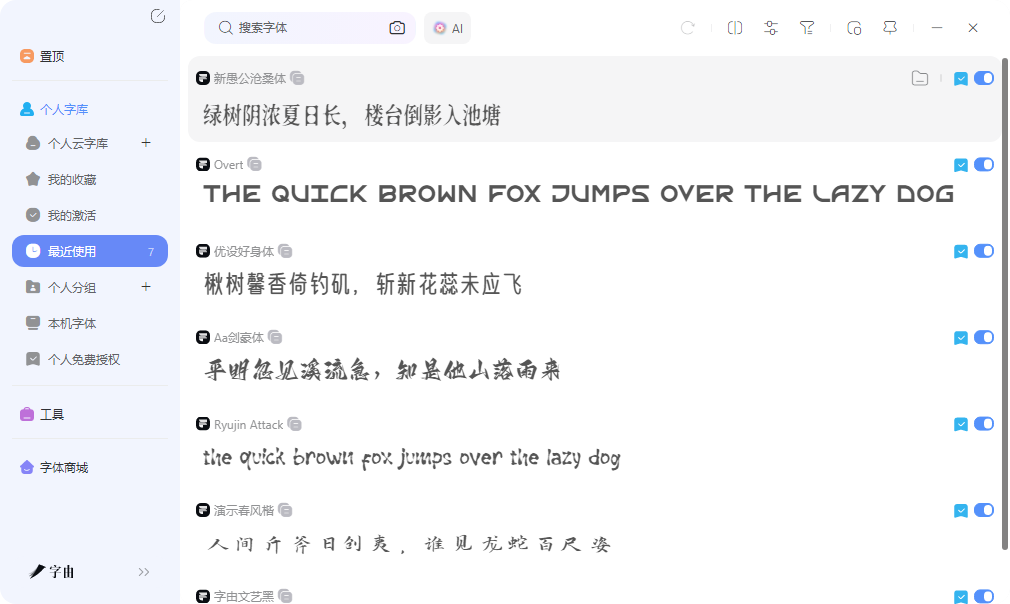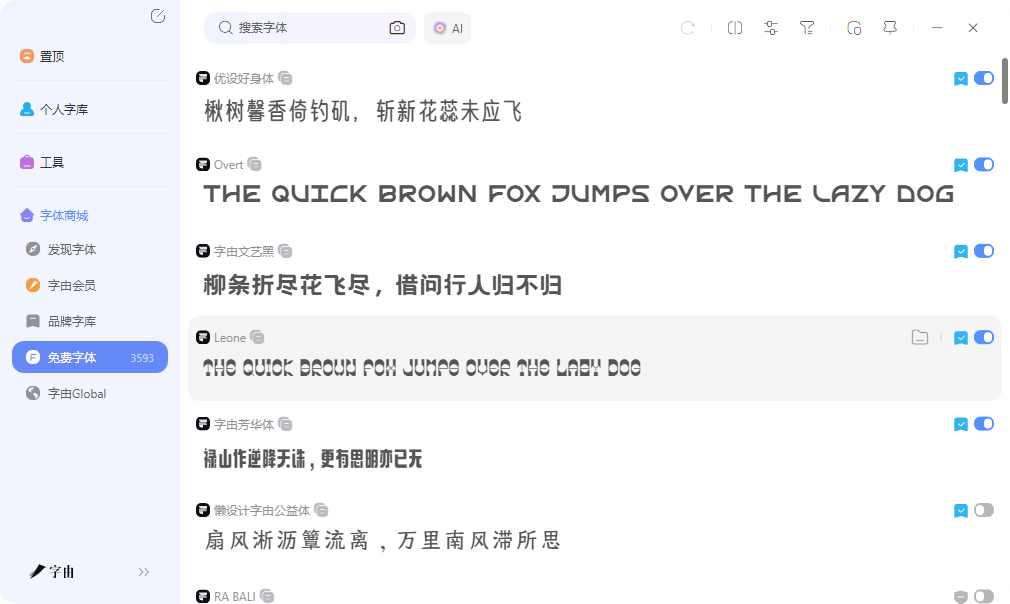
免费的字体下载网站,海量资源加精选推荐
很多人找字体时有个习惯,打开收藏夹里十几个网站逐个翻,最后下载了一堆重复的资源,硬盘里存了上千款字体,真到用的时候还是不知道选哪个。更麻烦的是授权问题,有些字体看着免费,实际仅限个人使用,真用到商业项目上才发现要补费用。其实找字体不是越多越好,关键是渠道靠谱、分类清晰、授权明确。这篇文章整理了五个免费的字体下载网站,从海量开源库到精选独立厂牌都有覆盖,帮你缩小搜索范围,把时间花在设计本身而不是找字上。
字由在字体管理上的思路比较贴近实际工作流,设计师通常同时处理多个项目,每个项目的字体需求不一样,A项目要商务黑体,B项目要文艺手写体,C项目要科技感的无衬线体。字由的收藏分组功能可以按项目建立独立的字体文件夹,把每个项目常用的几款字体归到一起,切换项目时直接打开对应分组,不需要在庞大的字体库里重新翻找。分组名称可以自定义,比如电商大促、品牌VI、社交媒体等,一目了然。
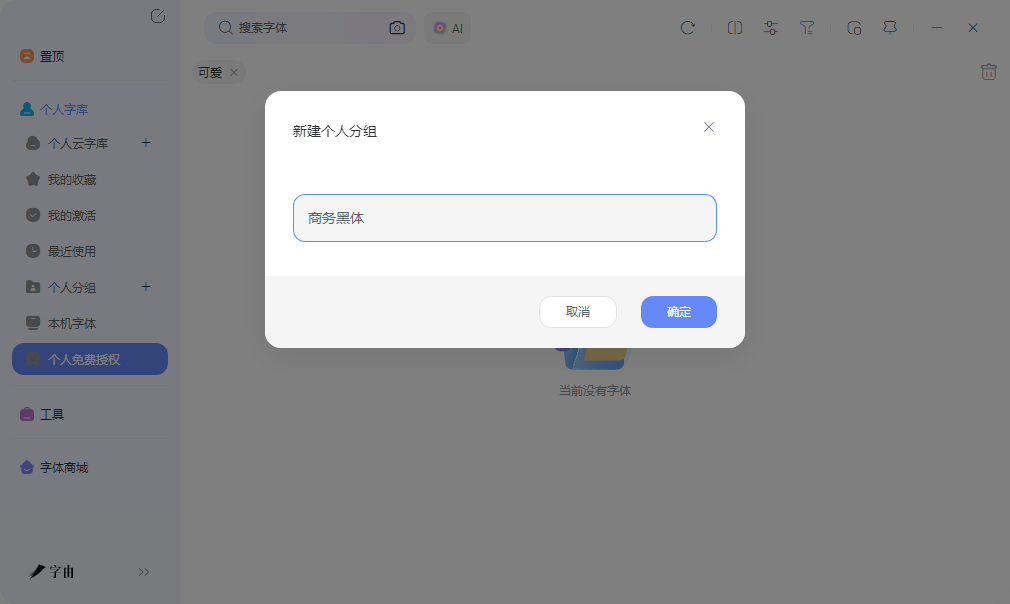
网页版和客户端的数据是互通的。习惯在浏览器里浏览的人可以先在网页版里看到合适的字体,点收藏后,打开客户端就能直接激活使用。反过来在客户端里收藏的字体,网页版里也能看到。这种双端协同让找字和用字不需要绑定在同一台设备上,临时在其他电脑上打开浏览器就能浏览和收藏,回家再激活使用。对于经常在不同设备之间切换的设计师来说,这种灵活性比较实用。
免费商用的字体超过三千款,卡片上直接标注授权类型。对于需要快速确认能不能商用的场景,这个标注省了不少时间。这些字体来自优设、阿里妈妈、汉仪、蒙纳等正规厂商,上架前经过授权审核,企业用户用起来比较放心。预览框支持输入中文文案,调整字号和背景色,看到真实效果再决定是否加入收藏分组,避免了收藏后发现不合适再删除的反复操作。
2、Open Foundry
Open Foundry是一个开源字体平台,定位偏向精选而非海量。平台上的字体数量不算多,但每一款都经过筛选,品质比较高。字体风格偏向现代设计,很多适合做网页、界面和品牌视觉项目。所有字体采用开源协议,允许商用和修改,不需要额外付费或联系作者。
平台上的字体展示方式比较直观,每款都有详细的字符集展示和实际应用示例。对于想了解一款字体在真实项目中表现的设计师来说,这种展示比纯预览图更有参考价值。Open Foundry作为免费的字体下载网站,其价值在于少而精的选品逻辑,不需要在大量低质量资源里翻找,适合对字体品质有一定要求、但又不想付费购买商业字体的用户。下载流程简洁,获取的字体文件为标准格式,安装后在设计软件里直接调用。
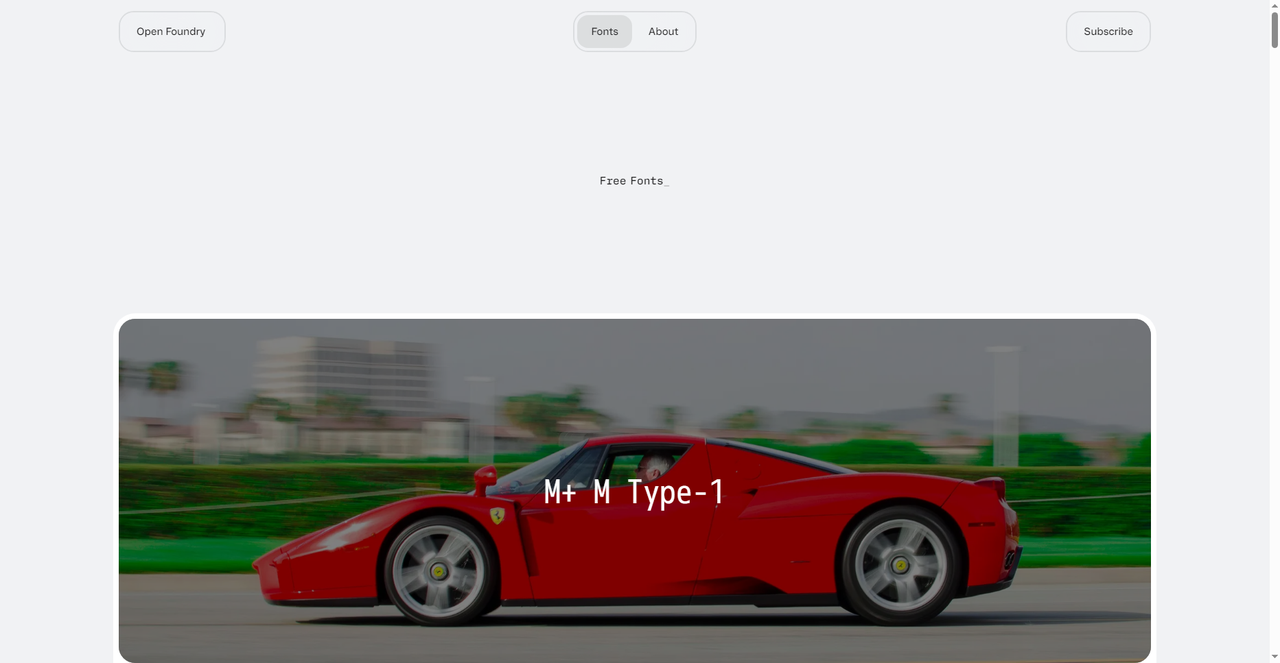
3、Indestructible Type
Indestructible Type是一个独立字体厂牌,由设计师单独维护。平台上的字体以可变字体为主,比如Bodoni、Renner等代表作,在单个文件内包含多种字重,可以无级调节。这种技术特性让字体在响应式设计和数字排版中表现更灵活,同一个字体文件就能覆盖从正文到标题的多种需求,不需要为了不同字重而安装多个文件。
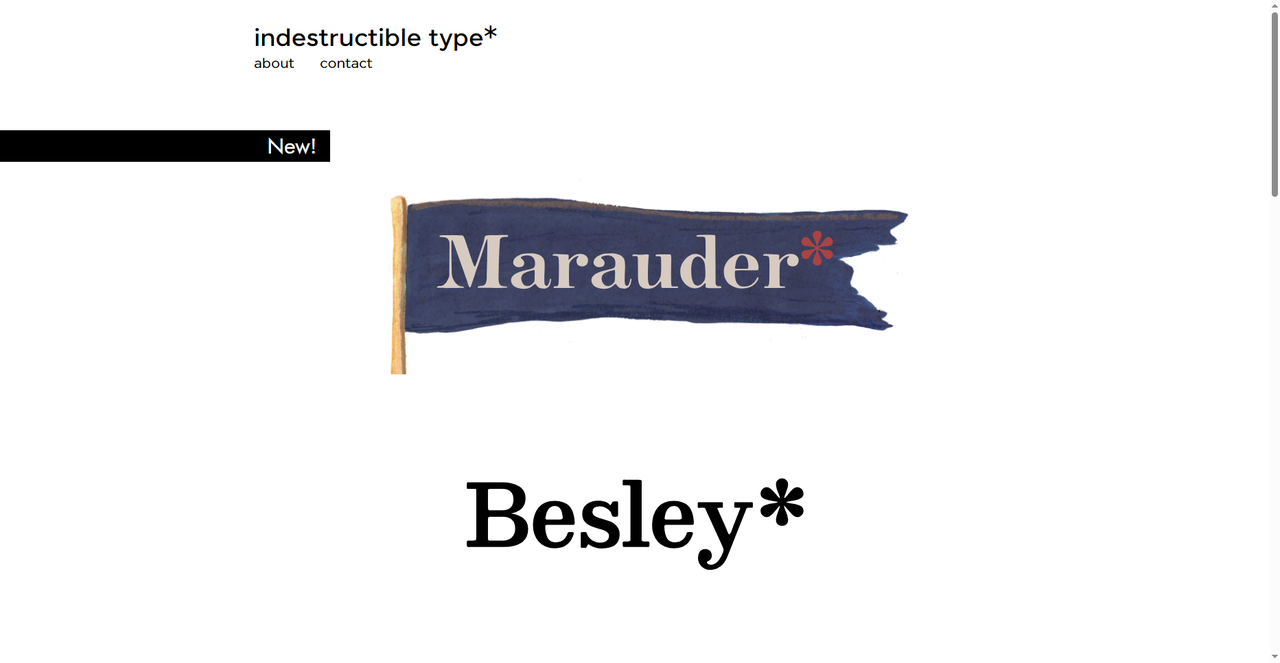
4、Unblast
Unblast是一个综合设计资源站,除了字体外还提供模板、样机、图形等素材。它的字体板块收录了不少免费商用字体,风格偏向现代商业设计,很多适合做社交媒体、电商和品牌项目的字体。每款字体都有清晰的展示图和授权说明,下载按钮直接获取标准格式的字体文件。
对于需要免费的字体下载网站、同时还想在同一平台补充其他设计素材的用户来说,Unblast的资源多样性比较方便。不需要在多个网站之间切换,找字体的时候顺便看看有没有合适的模板或样机,能省下不少时间。网站更新频率不错,定期来逛能看到新上架的资源。字体分类比较直观,可以按风格标签逐步筛选,找特定气质的字体时效率较高。
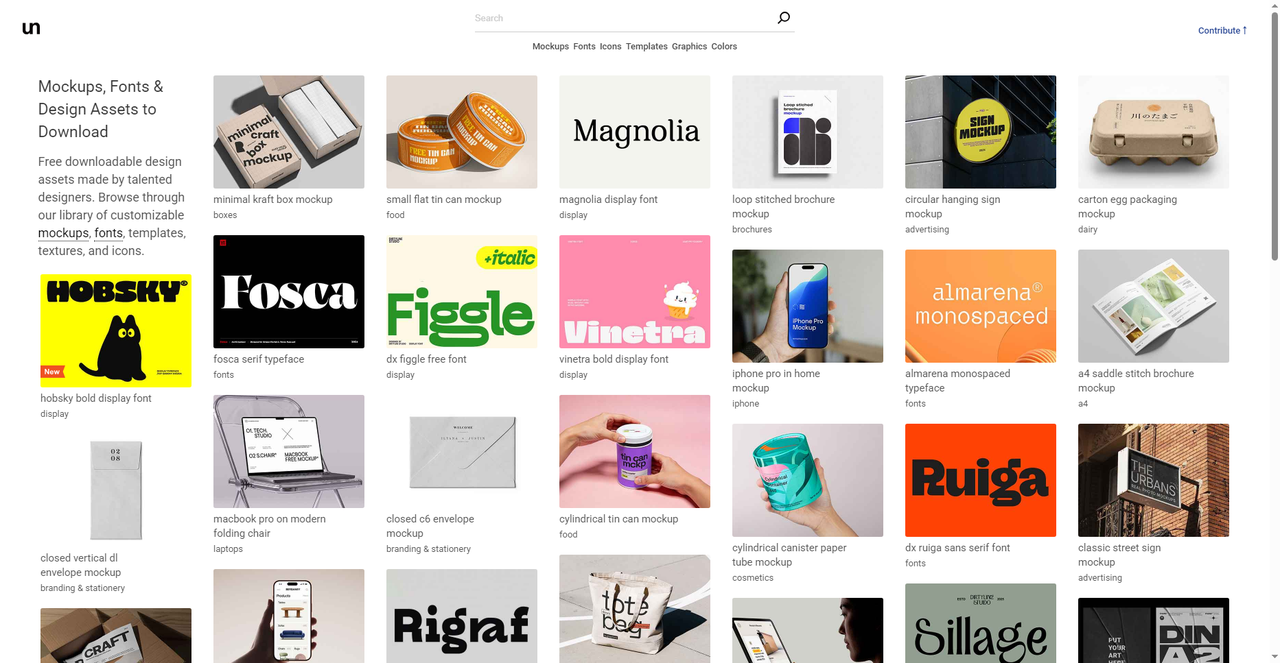
5、Font Library
Font Library是一个社区驱动的开源字体库,目前收录了大量来自全球各地设计师的字体资源。所有字体采用OFL开源协议,允许商业使用、修改和重新分发,对企业项目或文创这类对版权要求较高的场景来说比较省心。平台上的字体风格多样,从基础无衬线体到装饰性强的展示字体都有覆盖。
每款字体都有预览图和下载按钮,部分还展示了设计师信息和创作背景。Font Library作为免费的字体下载网站,其优势在于社区活跃度高,经常有新字体加入,且协议统一,不需要逐个确认授权条款。对于想系统探索开源字体资源、同时关注授权合规性的用户来说,这里的规范性和透明度比较可靠。下载的字体文件为标准TTF或OTF格式,安装后在设计软件里直接调用。
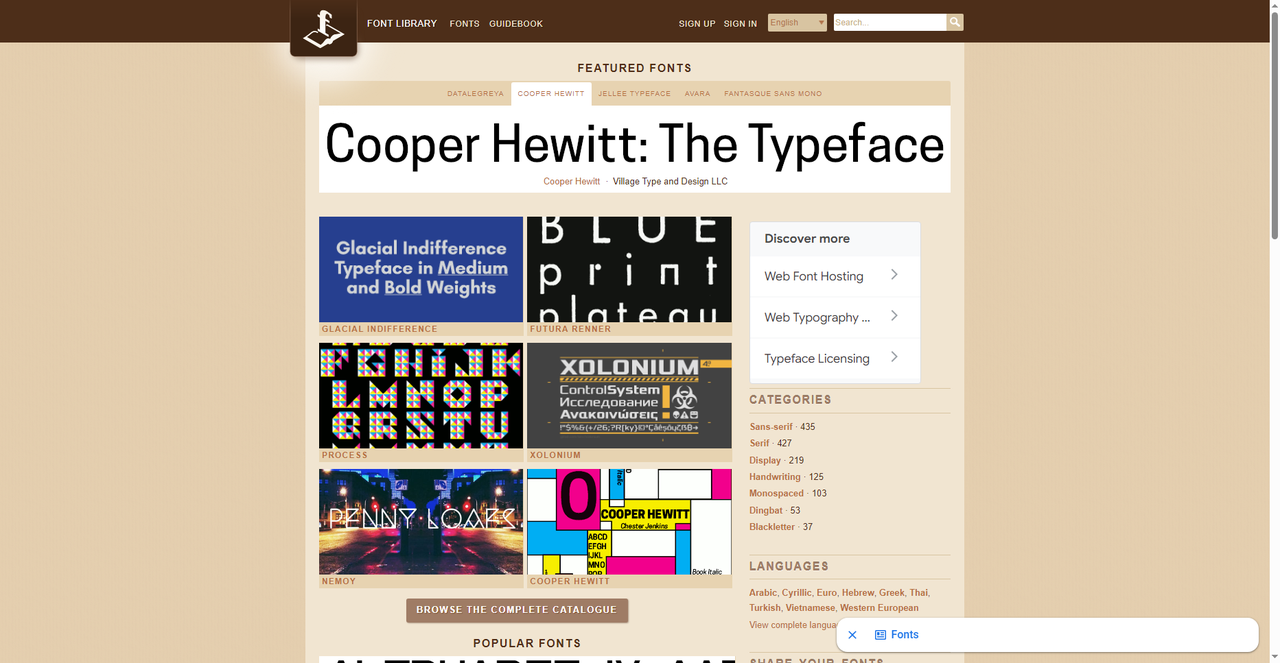
关于找字体,字由的项目分组和双端协同在管理层面比较实用,配合AI识字能快速确认未知字体的授权。Open Foundry和Indestructible Type在精选品质和可变字体技术方面各有优势,作为免费的字体下载网站中偏精品路线的选择。Unblast适合需要同时补充其他素材的情况。Font Library则是开源协议最放心的渠道之一。